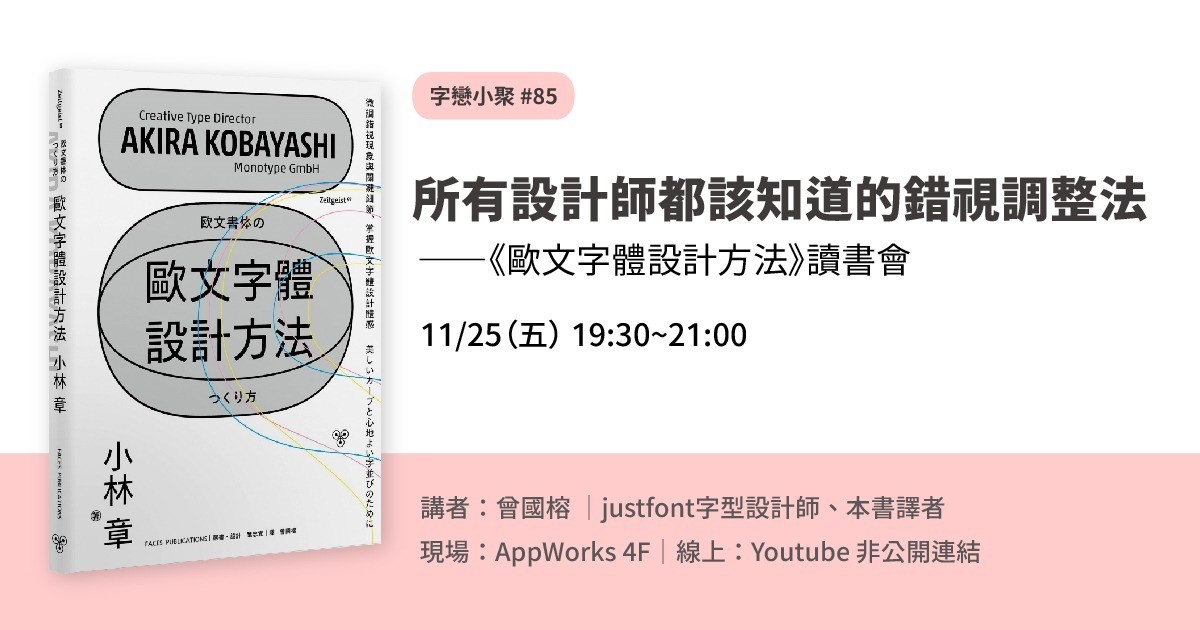
字戀小聚 #85|所有設計師都該知道的錯視調整法——《歐文字體設計方法》讀書會
集結歐文字體大師小林章三十年經驗而成的《歐文字體設計方法》,整理視覺錯視、歐文閱讀節奏、空間分配等細節的調整方法。是有標準字設計需求、排版需求、字體設計需求的設計師們,必須入手的參考書籍。
字戀小聚 #85 ,由本書譯者,也是 jf 字型設計師的曾國榕,介紹本書的正確打開方法。
什麼是視覺錯視?要相信自己的眼睛,還是相信數學與機器?歐文的節奏感怎麼看?又該怎麼應用在標準字與 LOGO 設計上?
除了由國榕分享,也邀請參與者事前許願想學的知識或技巧,一起來討論!
《歐文字體設計方法》適合字體設計師、有標準字設計需求的設計師、有歐文排版需求的設計師,以及文字造型學習者。技術含量可能有點高,但保證有收穫!